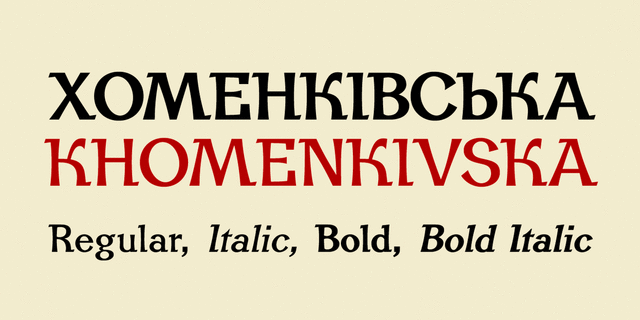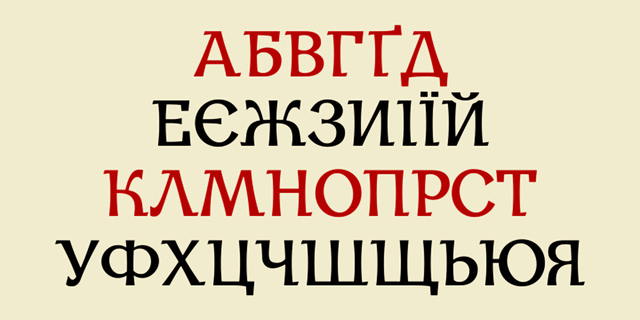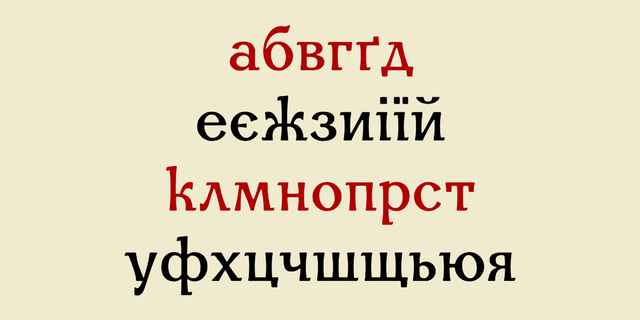
Знаменитая Хоменковская гарнитура, которая еще в советское время продолжала традицию шрифтов с асимметричными засечками (Георгия Нарбута), была завершена известным художником-графиком Василием Хоменко (1912-1984) в 1965 году. Долгое время она оставалась единственной наборной гарнитурой с украинским характером, а также воспроизводилась в декелях для художественно-оформительских работ.
Современная электронная версия была проработана и развита Геннадием Заречнюком. Трансформировавшись в качественную полноценную шрифтовую семью, она отвечает всем требованиям современности.
Шрифт прекрасно подходит для наборных текстов, хорошо читается в мелких кеглях, но, благодаря выразительному характеру, с успехом может быть применен и в акциденции.
Шрифт разработали Геннадий Заречнюк и Виктор Харик по мотивам гарнитуры Василия Хоменко в 2010 году.